Top 15 font chữ tiêu đề Việt hóa nổi bật cho poster, banner, thumbnail
Danh sách dưới đây tập trung hoàn toàn vào các font TH Việt hóa. Mỗi font mang một cá tính riêng, từ mạnh mẽ, công nghệ, thể thao đến retro, hoạt hình, văn hóa
Một thiết kế có thể sở hữu hình ảnh đẹp, màu sắc bắt mắt và bố cục chỉn chu nhưng vẫn thiếu sức hút nếu phần tiêu đề quá mờ nhạt. Với poster, banner hay thumbnail, người xem thường chỉ dành vài giây để quyết định có tiếp tục đọc hay không. Vì vậy, font chữ tiêu đề không chỉ làm nhiệm vụ hiển thị nội dung mà còn phải tạo điểm dừng thị giác, gợi đúng cảm xúc và giúp thông điệp được nhận ra ngay lập tức.
Danh sách dưới đây tập trung hoàn toàn vào các font TH Việt hóa. Mỗi font mang một cá tính riêng, từ mạnh mẽ, công nghệ, thể thao đến retro, hoạt hình, văn hóa Á Đông và phong cách quân đội. Các font đều có trang tải riêng trên Fontdep.vn, hỗ trợ tiếng Việt và phù hợp để làm headline cỡ lớn. Đặc biệt, 15 lựa chọn này không trùng với những font đã được giới thiệu trong các bài trước của kế hoạch content.
Cách chọn font chữ tiêu đề cho đúng thiết kế
Ưu tiên khả năng đọc trong ba giây đầu tiên
Tiêu đề trên thumbnail và banner thường được xem ở kích thước nhỏ, nhất là khi người dùng lướt bằng điện thoại. Font đẹp nhưng quá nhiều chi tiết có thể khiến chữ dính vào nhau hoặc dấu tiếng Việt khó nhìn. Hãy thử thu nhỏ thiết kế xuống khoảng 25%: nếu vẫn đọc được cụm từ chính, font đang làm tốt nhiệm vụ của nó.
Chọn cá tính font phù hợp với nội dung
Font thể thao cần cảm giác tốc độ và năng lượng; font cho nội dung trẻ em nên tròn trịa, thân thiện; poster kinh dị cần đường nét sắc, tối và kịch tính. Sự đồng điệu giữa kiểu chữ và chủ đề giúp người xem hiểu tinh thần thiết kế trước cả khi đọc hết câu.
Chỉ dùng font display cho phần cần nhấn
Phần lớn các font trong danh sách là display font, được tạo ra để nổi bật ở kích thước lớn. Chúng phù hợp cho headline, tên chiến dịch, giá khuyến mãi hoặc một câu CTA ngắn. Đoạn mô tả, thời gian, địa chỉ và điều kiện chương trình nên dùng một font sans-serif đơn giản để bảo đảm độ rõ ràng.
Kiểm tra dấu tiếng Việt trước khi xuất file
Hãy thử những cụm có nhiều dấu như “Ưu đãi đặc biệt”, “Giảm giá cuối tuần”, “Khám phá ngay” hoặc “Sự kiện tháng Bảy”. Cách kiểm tra này giúp phát hiện sớm tình trạng dấu chạm nét, lệch vị trí hoặc khoảng cách chữ chưa đều. Font TH Việt hóa đã được tối ưu cho tiếng Việt, nhưng bạn vẫn nên kiểm tra theo đúng cỡ chữ và phần mềm đang sử dụng.
Top 15 font chữ tiêu đề TH Việt hóa đáng thử
1. TH Joypor - tiêu đề phong cách Hàn Quốc hiện đại
TH Joypor mô phỏng tinh thần của chữ Hangeul qua hệ ký tự Latin, tạo cảm giác Á Đông hiện đại nhưng vẫn dễ nhận diện. Cấu trúc hình học vuông vức kết hợp các góc bo nhẹ giúp font vừa cá tính vừa thân thiện, đặc biệt phù hợp với nội dung hướng đến giới trẻ.
Bạn có thể dùng TH Joypor cho poster K-pop, menu món Hàn, bao bì mỹ phẩm, banner thời trang đường phố hoặc thumbnail khám phá văn hóa Hàn Quốc. Để font phát huy hiệu quả, nên đặt tiêu đề ngắn trên nền ít chi tiết và tăng khoảng cách giữa các dòng.
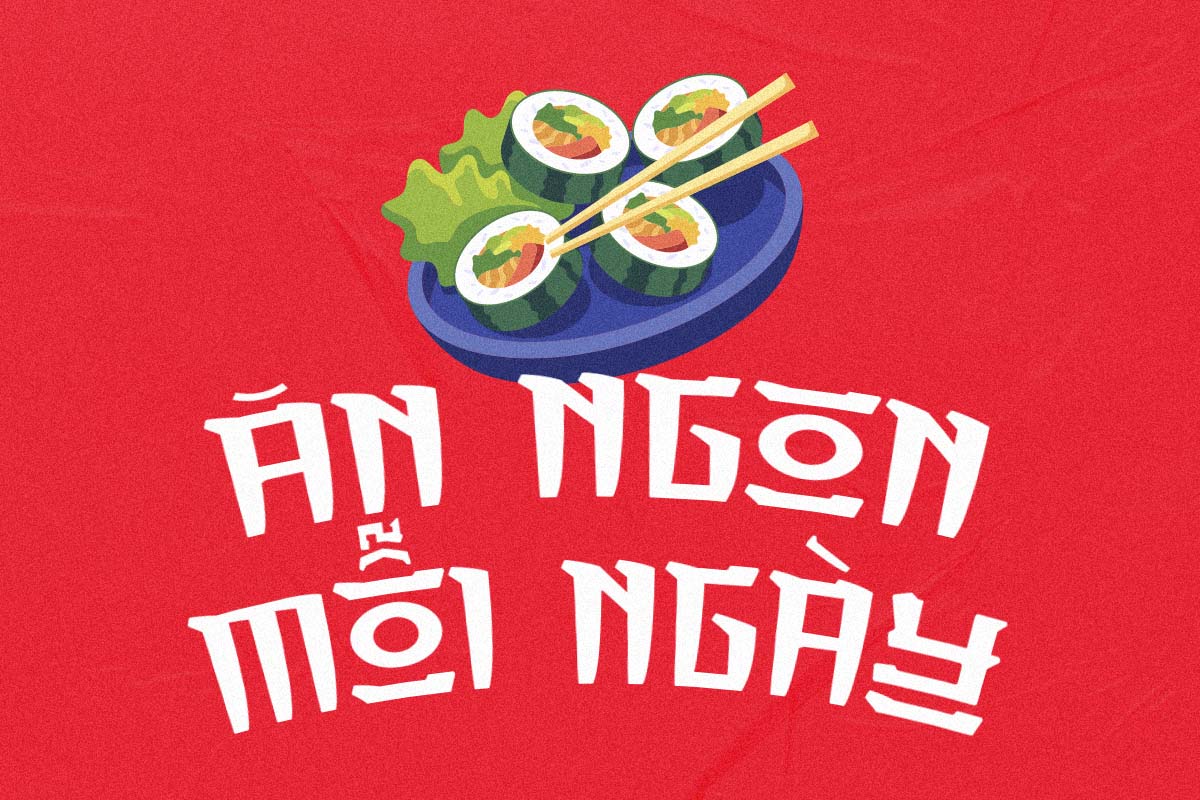
2. TH Geardive - font tiêu đề thể thao và tương lai
TH Geardive có dáng chữ nghiêng, các đường cắt sắc và cấu trúc chắc chắn, gợi cảm giác tốc độ ngay từ ánh nhìn đầu tiên. Đây là lựa chọn tốt khi thiết kế cần truyền tải tinh thần thi đấu, chuyển động hoặc công nghệ hiệu suất cao.
Font phù hợp với banner giải đấu esports, poster thể thao, thumbnail đánh giá xe, sự kiện đua tốc độ và nhận diện đội nhóm. Hãy phối TH Geardive với màu tương phản mạnh, nhưng hạn chế thêm nhiều hiệu ứng viền vì bản thân chữ đã có đủ lực thị giác.
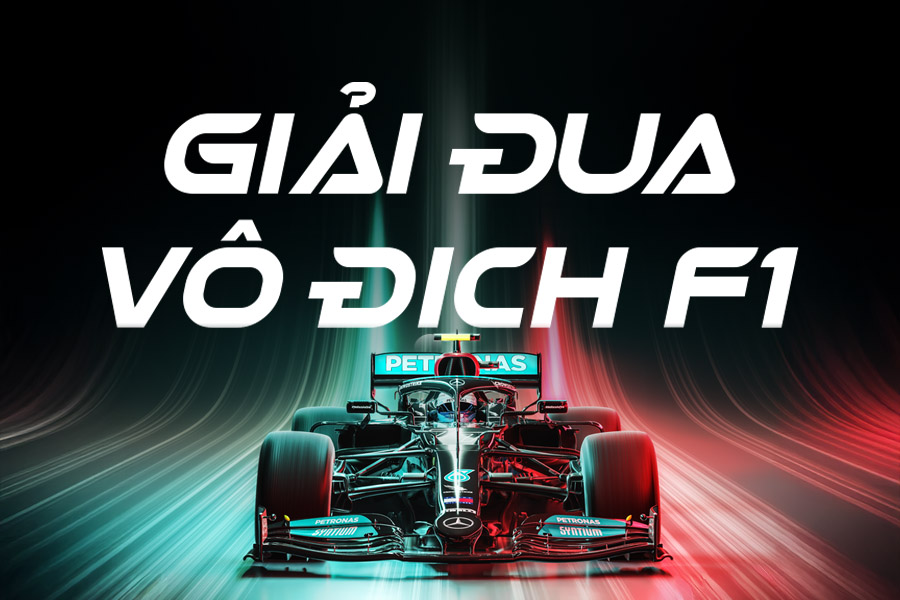
3. TH Elmirad - điểm nhấn Ả Rập huyền bí
TH Elmirad lấy cảm hứng từ thư pháp Trung Đông với những nét móc, đường cong và độ tương phản dày mỏng giàu tính trang trí. Kiểu chữ tạo cảm giác huyền bí, trang trọng và khác biệt rõ rệt so với những font display Latin thông thường.
TH Elmirad thích hợp cho poster chủ đề sa mạc, du lịch Trung Đông, game nhập vai, phim cổ trang, nhà hàng hoặc bao bì sản phẩm truyền thống. Nên dùng font cho một cụm tiêu đề ngắn và dành nhiều khoảng thở xung quanh để các chi tiết đặc trưng không bị rối.
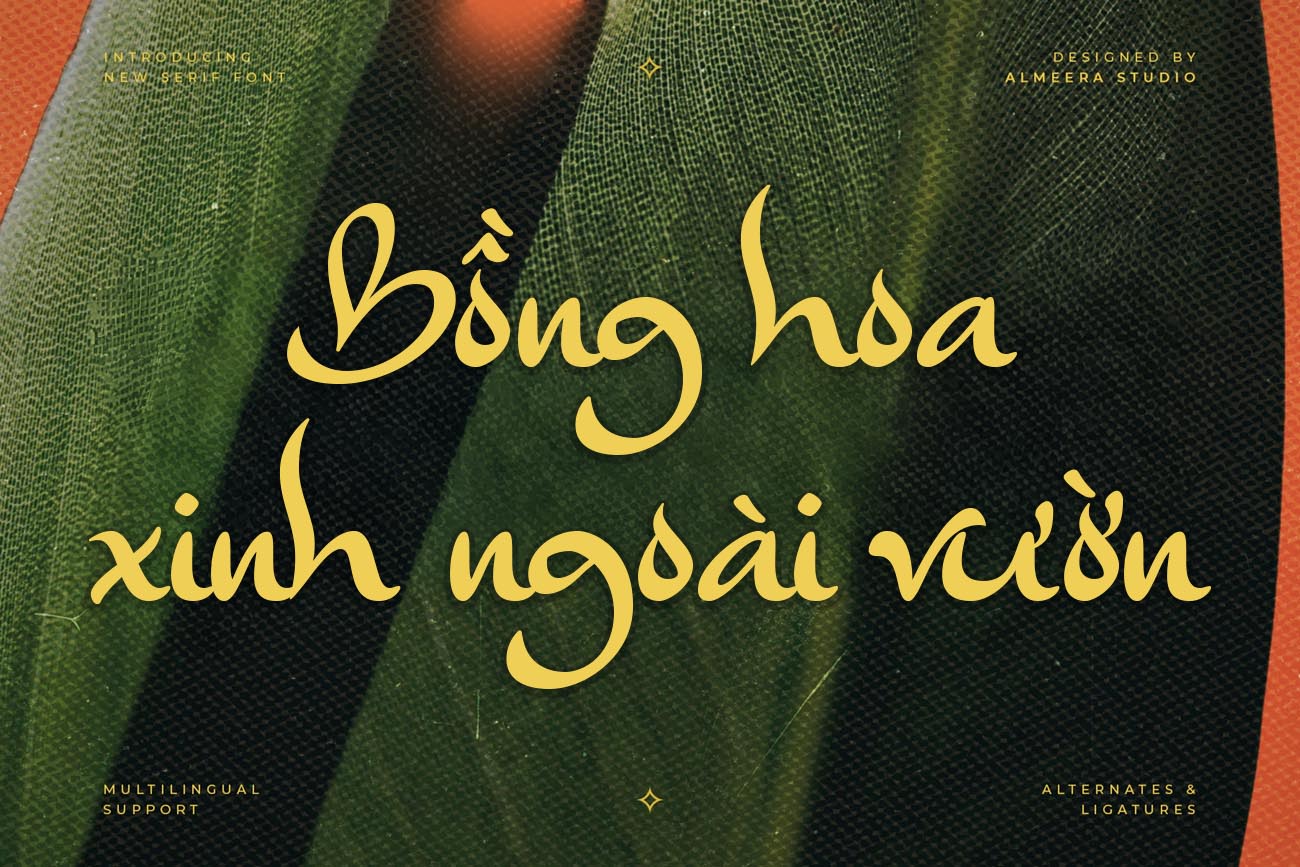
4. TH Modirgan - headline Gothic cho nội dung kinh dị
TH Modirgan mang cấu trúc Gothic với đường nét sắc, gai góc và sắc thái u tối. Font tạo không khí kịch tính rất nhanh, vì vậy phù hợp khi tiêu đề cần khiến người xem liên tưởng đến bí ẩn, bóng tối hoặc một câu chuyện căng thẳng.
Bạn có thể ứng dụng font cho poster Halloween, bìa truyện trinh thám, thumbnail kể chuyện kinh dị, album metal hoặc chiến dịch thời trang darkwear. Không nên viết cả đoạn dài bằng TH Modirgan; chỉ một tiêu đề lớn kết hợp nền tối và màu nhấn đỏ hoặc trắng đã đủ hiệu quả.
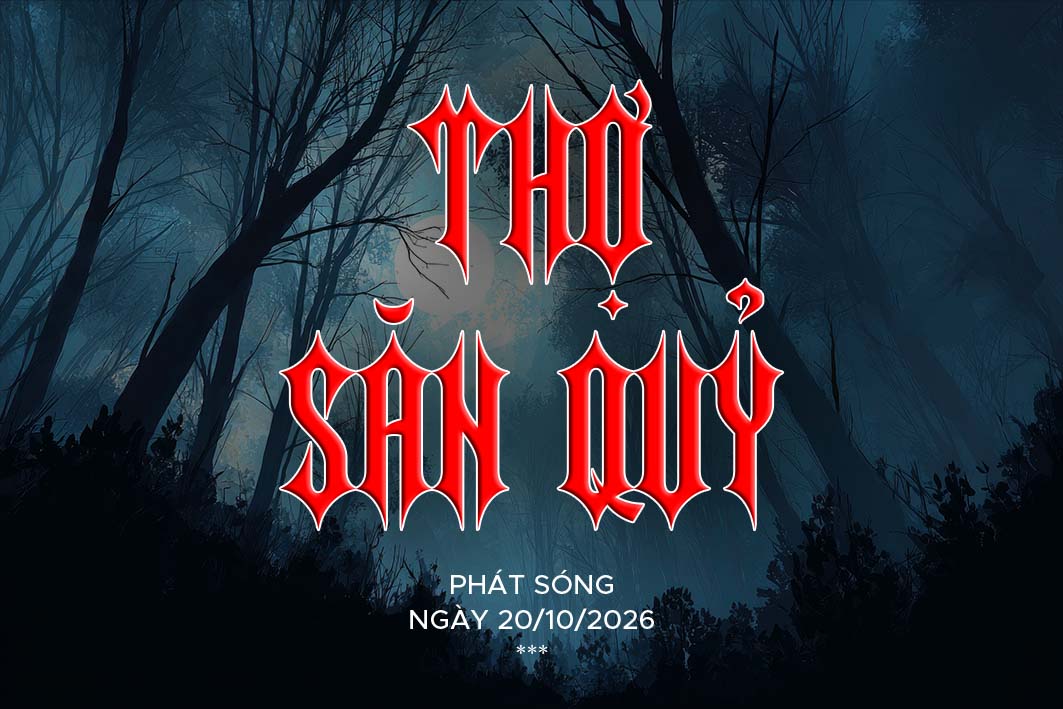
5. TH Tenkai - nét cọ Nhật Bản giàu năng lượng
TH Tenkai mô phỏng những nét cọ khô mạnh mẽ, dứt khoát và có độ đậm nhạt tự nhiên. Kiểu chữ mang tinh thần Nhật Bản cổ xưa, đồng thời giữ được vẻ phóng khoáng cần thiết cho các thiết kế hiện đại.
Font đặc biệt hợp với poster võ thuật, nhà hàng sushi hoặc ramen, thumbnail game kiếm hiệp, sự kiện văn hóa Nhật và thiết kế áo thun. Khi sử dụng, hãy tránh nền quá nhiều texture vì bề mặt nét cọ của font đã là một yếu tố trang trí nổi bật.
Xem mẫu và tải font TH Tenkai Việt hóa.
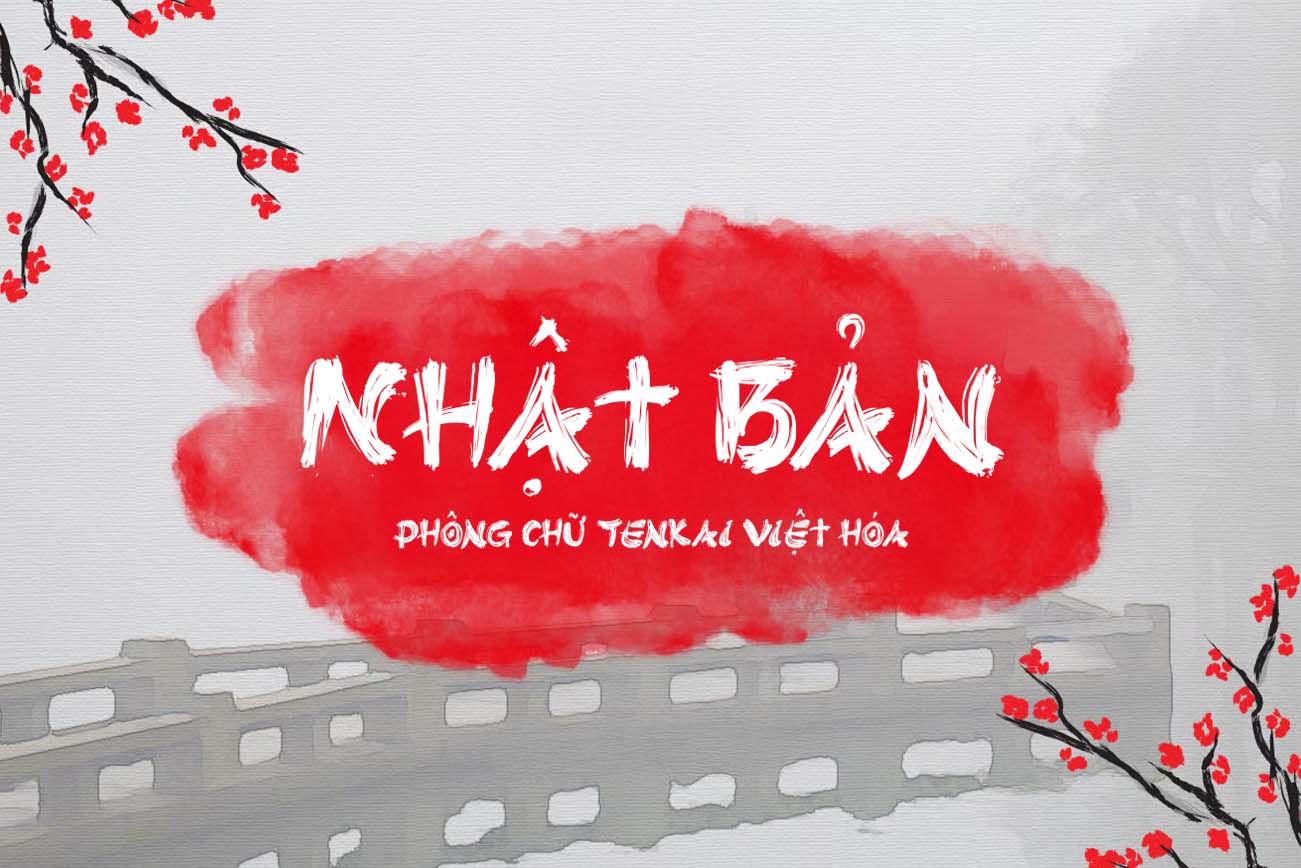
6. TH Throwback Glorious - chất brush retro phóng khoáng
TH Throwback Glorious kết hợp tinh thần retro với hiệu ứng cọ vẽ, tạo cảm giác thủ công, khỏe khoắn và giàu chuyển động. Font có khả năng biến một cụm chữ ngắn thành điểm nhấn giống như lettering được vẽ riêng cho thiết kế.
Đây là lựa chọn đáng thử cho poster âm nhạc, banner du lịch, thumbnail khám phá, nhãn đồ uống hoặc chiến dịch thời trang đường phố. Font phối tốt với ảnh đen trắng, màu đỏ gạch, vàng cũ hoặc xanh đậm. Hãy giữ phần chữ phụ thật gọn để headline không bị cạnh tranh.
Xem mẫu và tải font TH Throwback Glorious Việt hóa.
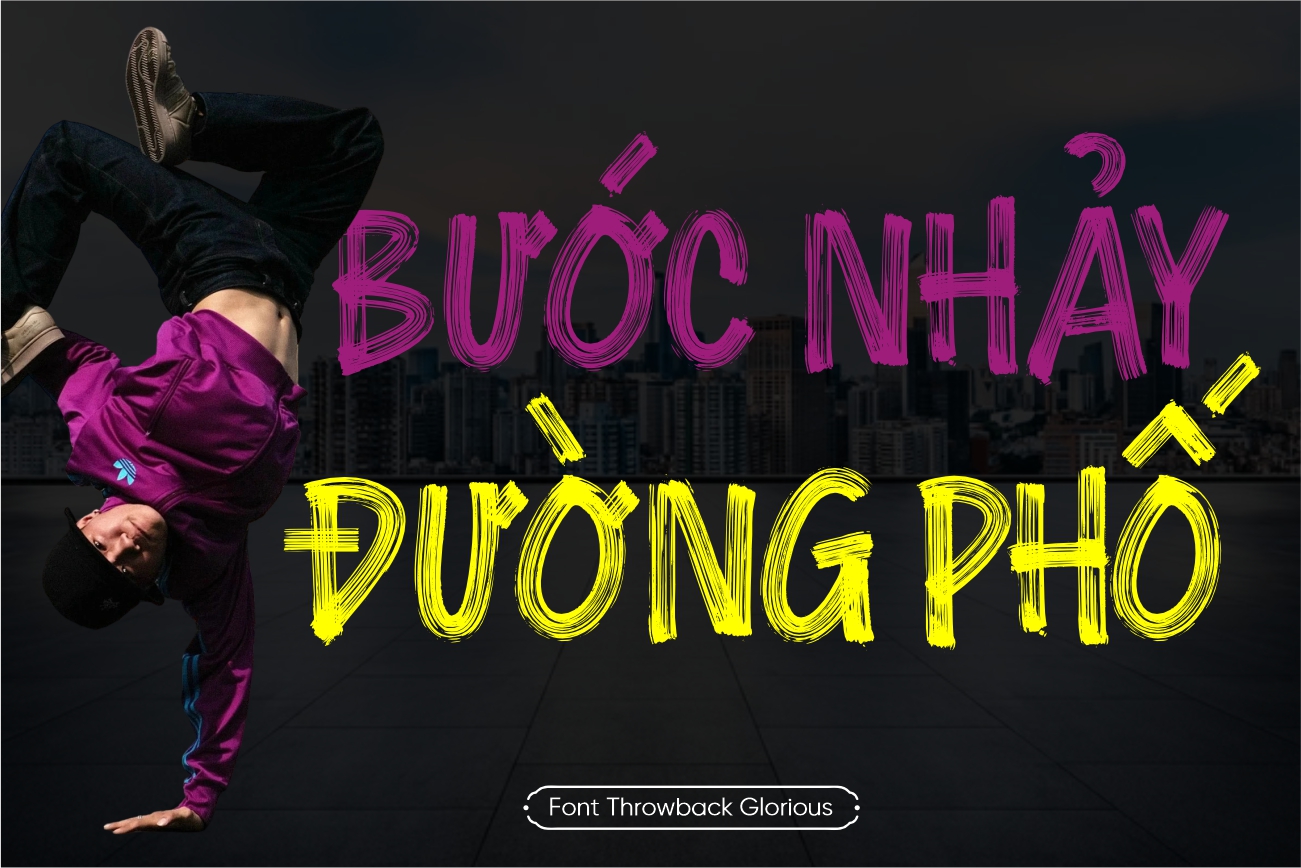
7. TH Seona Display - tiêu đề công nghệ gọn và sắc
TH Seona Display phù hợp với những thiết kế cần cảm giác kỹ thuật số, hiện đại và có định hướng tương lai. Hình khối chữ rõ ràng giúp headline nổi bật trên banner ngang, thumbnail hoặc giao diện quảng bá sản phẩm công nghệ.
Bạn có thể dùng font cho sự kiện AI, ra mắt thiết bị, giải đấu game, khóa học công nghệ và nội dung khoa học viễn tưởng. Cách phối an toàn là dùng TH Seona Display cho tiêu đề, kết hợp font sans-serif trung tính cho thông số và mô tả, đồng thời giữ bảng màu có độ tương phản cao.
Xem mẫu và tải font TH Seona Display Việt hóa.
8. TH Acttime - script đậm cho thể thao và phiêu lưu
TH Acttime là script font có nét dày, độ nghiêng vừa phải và các đầu nét dứt khoát. Sự kết hợp giữa phong cách retro và tinh thần thể thao khiến font vừa có tính chuyển động, vừa giữ được cảm giác thủ công gần gũi.
Font phù hợp với logo đội nhóm, poster du lịch, banner streetwear, bìa tạp chí thể thao hoặc thumbnail hành trình. Vì chữ có nhiều chuyển động, bạn nên dùng cho tiêu đề từ hai đến sáu từ, tránh viết toàn bộ bằng chữ hoa và không đặt quá sát các thành phần khác.
Xem mẫu và tải font TH Acttime Việt hóa.
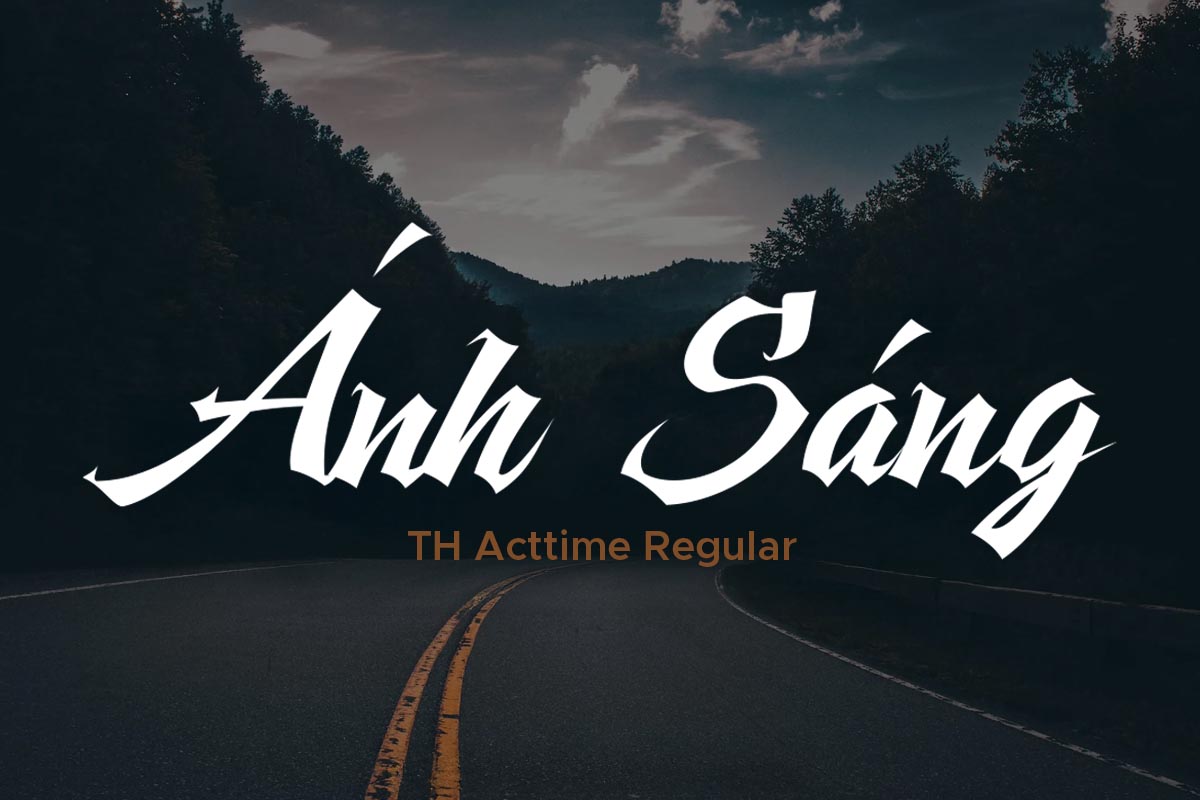
9. TH Nhat Ban 1 - dấu ấn lịch sử Nhật Bản
TH Nhat Ban 1 mang dáng vẻ trang trí rõ nét, phù hợp với các tiêu đề cần gợi không khí lịch sử và văn hóa Nhật. Font giúp thiết kế thoát khỏi cảm giác phổ thông mà không cần phụ thuộc quá nhiều vào biểu tượng minh họa.
Bạn có thể dùng font cho poster triển lãm, thumbnail kể chuyện lịch sử, bìa nội dung về samurai, menu nhà hàng Nhật hoặc thiết kế quà lưu niệm. Hãy dùng cỡ chữ lớn, dòng ngắn và phối cùng một font phụ đơn giản để thông tin ngày giờ, địa điểm vẫn dễ đọc.
Xem mẫu và tải font TH Nhat Ban 1 Việt hóa.
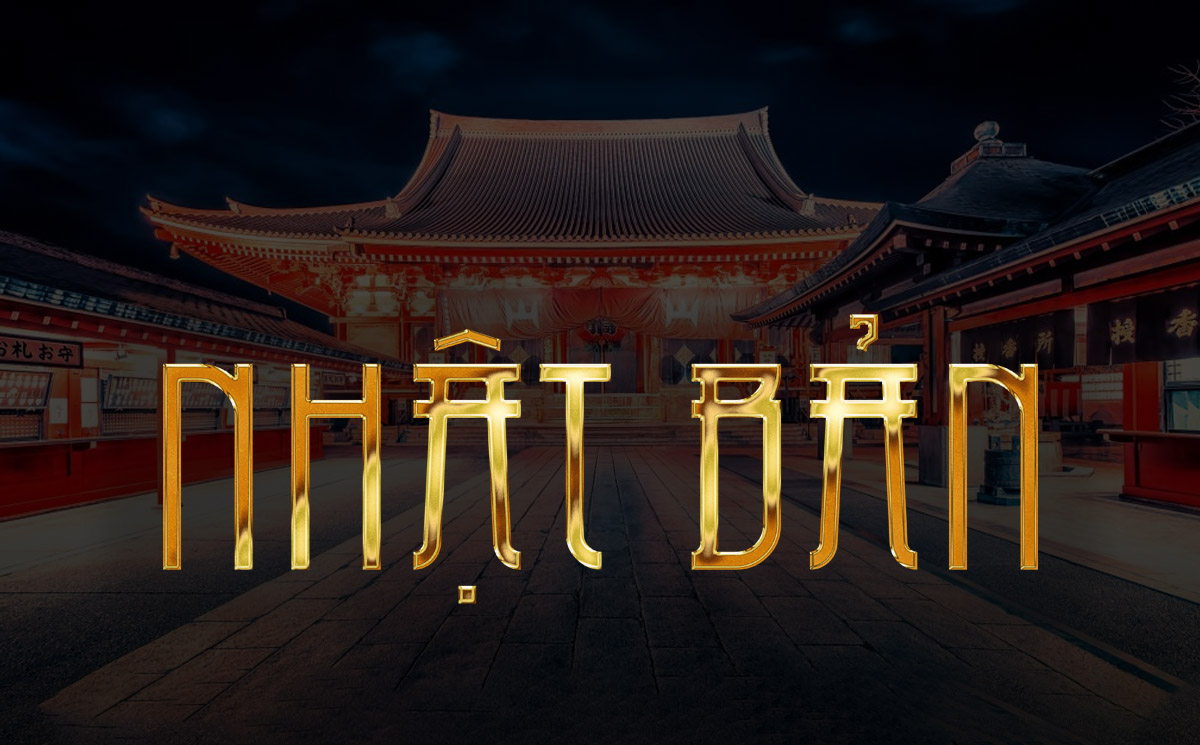
10. TH More Sugar - font hoạt hình tròn đầy, vui nhộn
TH More Sugar sở hữu các nét chữ dày, bo tròn và căng đầy như kẹo ngọt. Font dễ tạo thiện cảm, có độ nổi tốt và vẫn giữ được khả năng đọc ở những tiêu đề ngắn, rất hợp với nhóm khách hàng trẻ hoặc nội dung gia đình.
Font phù hợp cho poster đồ ăn vặt, banner lớp học, thumbnail thiếu nhi, bao bì bánh kẹo và chương trình minigame. Bạn có thể phối màu tươi sáng, nhưng nên giới hạn ở hai hoặc ba màu chính để thiết kế vui mắt mà không trở nên hỗn loạn.
Xem mẫu và tải font TH More Sugar Việt hóa.
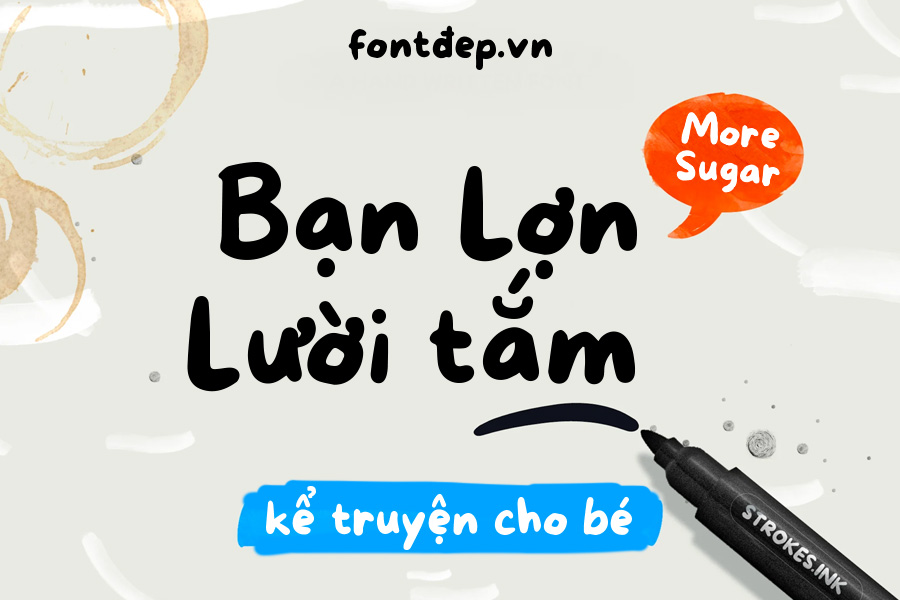
11. TH Juzho Kaizen - phong cách Nhật Bản mạnh và hiện đại
TH Juzho Kaizen mang cảm hứng Nhật Bản nhưng thể hiện theo hướng mạnh, hiện đại và dễ ứng dụng cho truyền thông đại chúng. Font tạo hình tiêu đề có bản sắc rõ mà vẫn phù hợp với poster, banner và thumbnail đương đại.
Bạn có thể dùng font cho chiến dịch ẩm thực Nhật, poster lễ hội, nội dung anime, game hoặc video khám phá văn hóa. Nên chọn một cụm từ chính làm tâm điểm, dùng màu đỏ, đen hoặc trắng có chủ đích và giữ phần nền đủ sạch để dáng chữ được nhìn rõ.
Xem mẫu và tải font TH Juzho Kaizen Việt hóa.
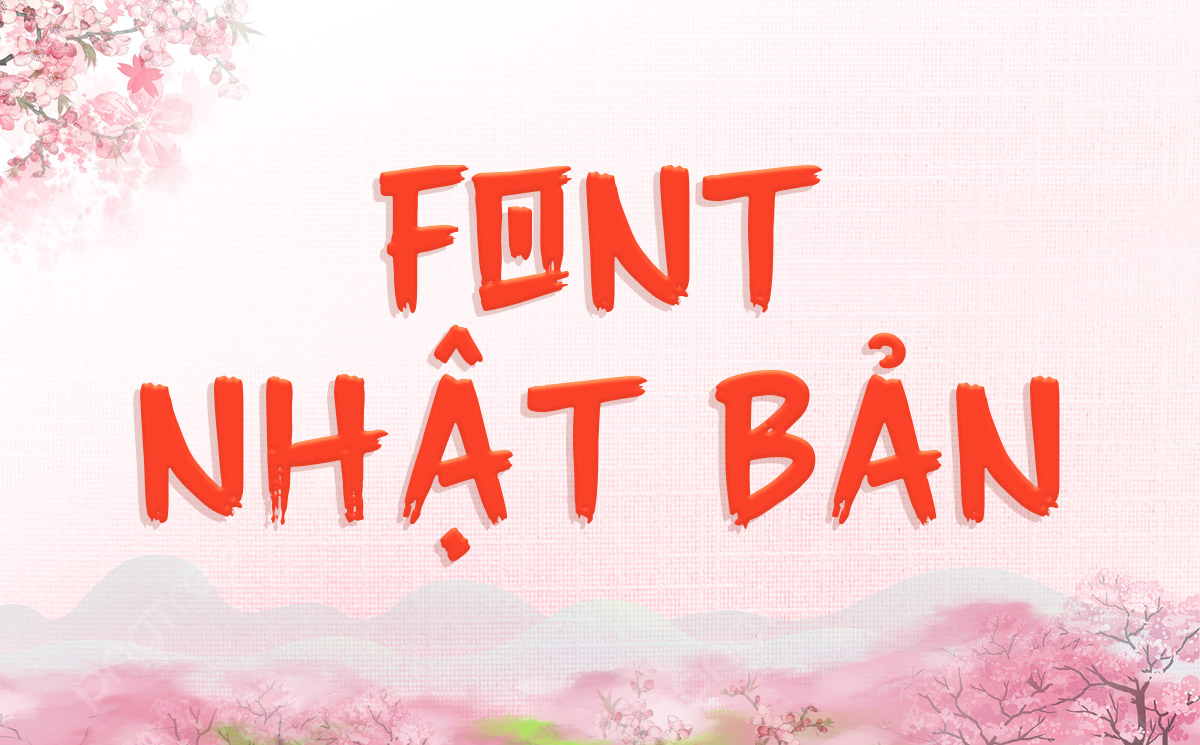
12. TH Bonitte - script retro mềm mại nhưng chắc nét
TH Bonitte có đường bút uốn lượn, nét dày và tinh thần retro rõ rệt. Hệ thống ligature và ký tự thay thế giúp tiêu đề có cảm giác như lettering thủ công, phù hợp với thiết kế muốn tạo sự gần gũi nhưng vẫn chuyên nghiệp.
Font phát huy tốt trên poster cafe, nhãn thực phẩm, banner local brand, bao bì thủ công hoặc thumbnail chủ đề lifestyle. Khi dùng TH Bonitte, hãy hạn chế hiệu ứng bóng và viền dày. Một màu chữ rõ trên nền tương phản thường cho kết quả tự nhiên hơn.
Xem mẫu và tải font TH Bonitte Việt hóa.
13. TH Cherry Feeling - chữ viết tay dễ thương, thân thiện
TH Cherry Feeling mang cảm giác viết tay nhẹ nhàng, tự nhiên và đáng yêu. Font không quá nặng nên thích hợp với những tiêu đề cần sự gần gũi, cảm xúc hoặc một chút ngẫu hứng cá nhân.
Font có thể dùng cho poster lớp học, thumbnail vlog, bài quote, banner đồ thủ công, nội dung mẹ và bé hoặc thiệp online. Để tăng độ rõ, hãy dùng nền đơn sắc và tránh kéo giãn chữ. Các tiêu đề dạng câu ngắn sẽ phù hợp hơn những cụm toàn chữ hoa.
Xem mẫu và tải font TH Cherry Feeling Việt hóa.
14. TH Glister - display sans condensed cứng cáp
TH Glister có dáng condensed, nét dày và hình khối gọn, giúp đưa nhiều ký tự vào một dòng mà vẫn tạo cảm giác mạnh mẽ. Đây là ưu điểm lớn khi thiết kế banner ngang hoặc thumbnail có không gian tiêu đề hạn chế.
Font phù hợp với poster sale, lookbook thời trang, banner sự kiện, bao bì sản phẩm và nội dung thương hiệu cần sự dứt khoát. Hãy ưu tiên chữ hoa cho cụm ngắn, tăng khoảng cách dòng và dùng font phụ có chiều rộng bình thường để tạo tương phản.
Xem mẫu và tải font TH Glister Việt hóa.
15. TH Army Rangers - stencil quân đội cho poster hành động
TH Army Rangers là display sans-serif dạng stencil, sử dụng các mảng cắt đặc trưng gợi liên tưởng đến quân phục, thùng hàng và thiết bị chiến thuật. Font được thiết kế theo hướng all-caps nên tiêu đề trông cứng cáp, kỷ luật và có sức nặng.
Đây là lựa chọn mạnh cho poster phim hành động, thumbnail game chiến thuật, banner đội nhóm, áo thun hoặc sự kiện thể lực. Font đã có chi tiết stencil rõ, vì vậy nên dùng màu phẳng và tránh thêm quá nhiều hiệu ứng 3D khiến cấu trúc chữ mất đi độ sắc nét.
Xem mẫu và tải font TH Army Rangers Việt hóa.
Công thức phối font tiêu đề dễ áp dụng
Font mạnh kết hợp sans-serif trung tính
Với poster thể thao, công nghệ hoặc hành động, hãy dùng TH Geardive, TH Glister, TH Seona Display hoặc TH Army Rangers cho headline. Phần mô tả nên chọn sans-serif đơn giản, ít cá tính và có nhiều độ đậm. Sự tương phản này giúp tiêu đề nổi bật mà thông tin phụ vẫn dễ đọc.
Font văn hóa kết hợp bố cục tối giản
TH Joypor, TH Tenkai, TH Juzho Kaizen và TH Elmirad đã mang dấu ấn văn hóa mạnh. Khi sử dụng, không cần thêm quá nhiều biểu tượng hay họa tiết trang trí. Một hình ảnh chính, một headline lớn và khoảng trắng hợp lý thường tạo kết quả thuyết phục hơn.
Font retro hoặc viết tay kết hợp chữ phụ gọn
TH Throwback Glorious, TH Acttime, TH Bonitte và TH Cherry Feeling phù hợp với thiết kế giàu cảm xúc. Hãy để font làm điểm nhấn ở tên thương hiệu hoặc câu tiêu đề, còn ngày tháng, giá bán và CTA nên chuyển sang font không chân rõ ràng.
Font hoạt hình cần kiểm soát màu sắc
Với TH More Sugar, bạn có thể dùng bảng màu vui tươi nhưng vẫn cần một màu nền chủ đạo, một màu chữ chính và một màu nhấn. Quá nhiều màu, viền, sticker và hiệu ứng cùng lúc sẽ làm giảm khả năng đọc của tiêu đề.
Những lỗi nên tránh khi dùng font tiêu đề
Không nên kéo dãn font theo chiều ngang hoặc chiều dọc vì thao tác này làm sai tỷ lệ chữ và khiến dấu tiếng Việt mất cân đối. Nếu cần lấp đầy không gian, hãy điều chỉnh cỡ chữ, tracking hoặc thay đổi độ rộng của khung chữ.
Đừng dùng hai font display có cá tính mạnh trong cùng một headline. Người xem sẽ khó xác định đâu là thông tin chính, trong khi thiết kế dễ trở nên rối. Một font nổi bật kết hợp một font trung tính thường là lựa chọn chắc chắn hơn.
Cuối cùng, cần kiểm tra thiết kế trên đúng kích thước sử dụng. Thumbnail đẹp khi phóng lớn chưa chắc còn rõ trên màn hình điện thoại; banner online đọc tốt chưa chắc phù hợp khi in ngoài trời. Hãy xuất bản nháp, thu nhỏ và thử trên nhiều nền trước khi chốt.
Font chữ tiêu đề tốt cần vừa tạo ấn tượng vừa phục vụ thông điệp. TH Geardive, TH Glister và TH Army Rangers phù hợp với thiết kế mạnh; TH Joypor, TH Tenkai và TH Juzho Kaizen tạo dấu ấn Á Đông; TH More Sugar và TH Cherry Feeling đem lại cảm giác thân thiện; trong khi TH Modirgan, TH Elmirad và TH Seona Display giúp các chủ đề đặc thù trở nên rõ nét hơn.